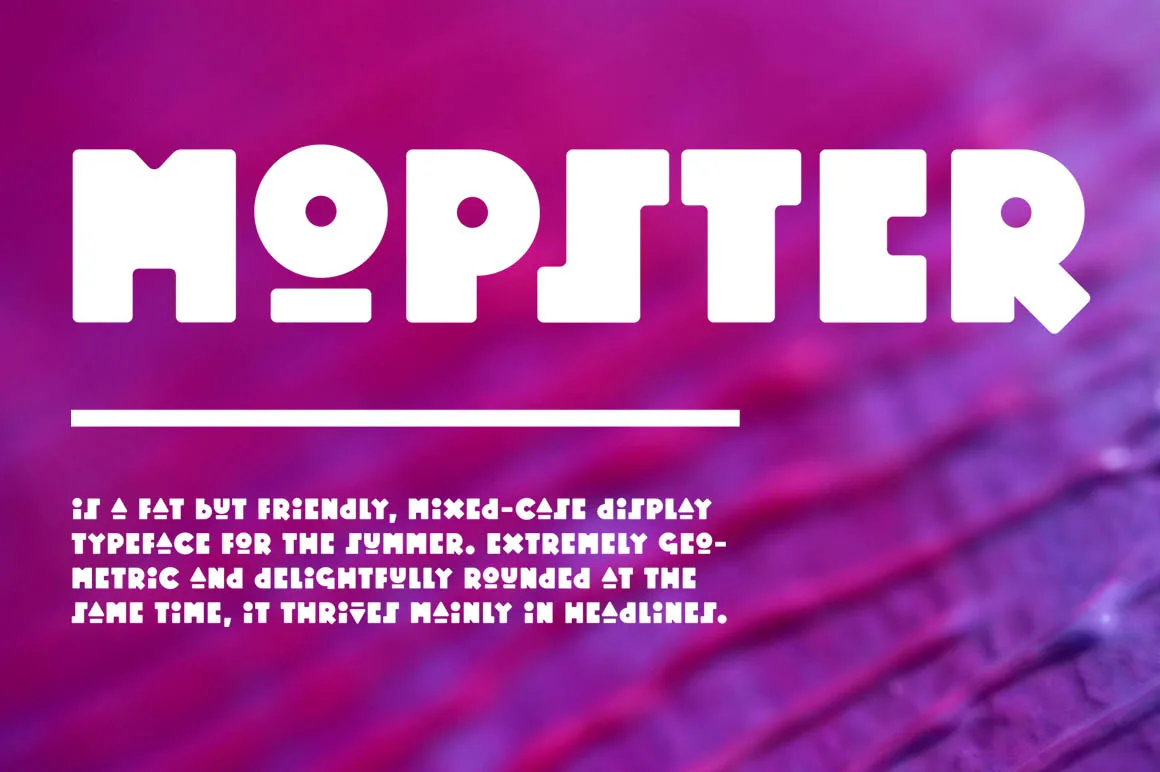
A MOPSTER é uma fantasia tipográfica robusta mas simpática para aquela época do ano que parece estar sempre à nossa espera – o verão. Inspirada pelo design geométrico e pelo toque alegre, ela se destaca especialmente nas menções em maiores tamanhos de texto. Esta fonte misturada é perfeitamente adaptada aos headlines, onde sua estrutura geométrica firme contrasta harmoniosamente com seu formato redondo e cheio. Ideal para desempenhar o papel de um sininho no meio do ambiente mais tradicionalmente serifado, a MOPSTER traz uma atmosfera descontraída e animada à qualquer projeto visual, seja ele em design gráfico ou em outras áreas que valorizam um estilo não tão convencional. Sempre ideal para dar aquele toque especial ao seu trabalho, é fácil de usar e torna o conteúdo imediatamente atraente aos olhos do leitor.